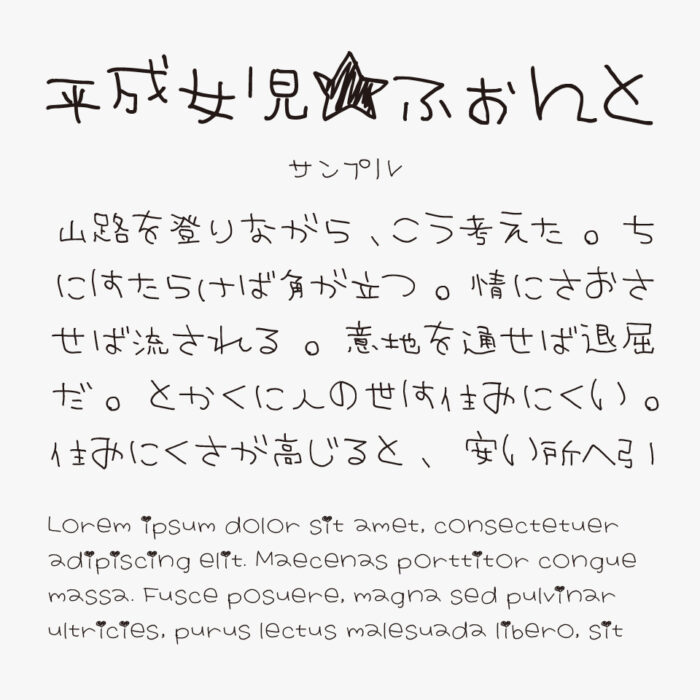
平成女児★ふぉんと
平成女児☆ふぉんとは、90年代〜2000年代の“プリクラ感”や“ギャル文字”を彷彿とさせる、ポップでラブリーな世界観の手書き風フォントです。
文字の中にハートが入っていたり、星マークがタイトルにあったりと、装飾にこだわりが感じられる手書き文字です。
文字の太さや線のブレが強めなので、あえての“平成レトロ”や“懐かしさ”を演出したいときにぴったりです。Y2K系、ギャル感、デコ文字風の演出に最適で、推し活グッズやZINEのタイトルなどにもおすすめのフォントです。
平成女児★ふぉんと